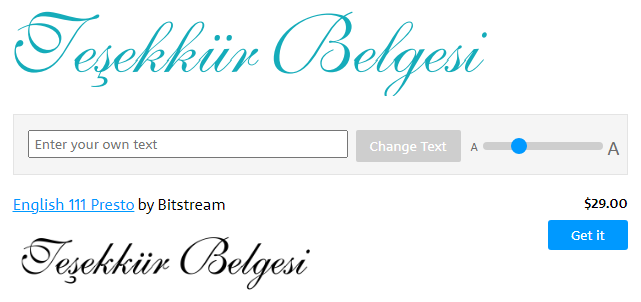
Görselde Bulunan Font Gerekli - R10+
Merhabalar, resimde ki fontu bulmam gerekiyor.
Bir çok siteden baktım fakat tam net cevabı vemiyor.
Yardımcı olabilir misiniz?
L harfleri farklı mesela bakarsanız
Bu sanırım kontrol eder misiniz?
What The Font sitesinden bulabilirsiniz hocam, aşağıda buldu mesela.
L harfleri farklı mesela bakarsanız
Birkaç harf tutmuyor ama en iyi uyan English 111 Presto k ve l harfleri boşluklu değil.
Shelley ile başlayan font ailesi var. Evde olmadığım için tam ismini hatırlayamadım. Bu değilse kesinlikle o aileden bir fonttur.
Sanırım bu hocam, fakat Ş harfini yazmıyor gibi bunda da